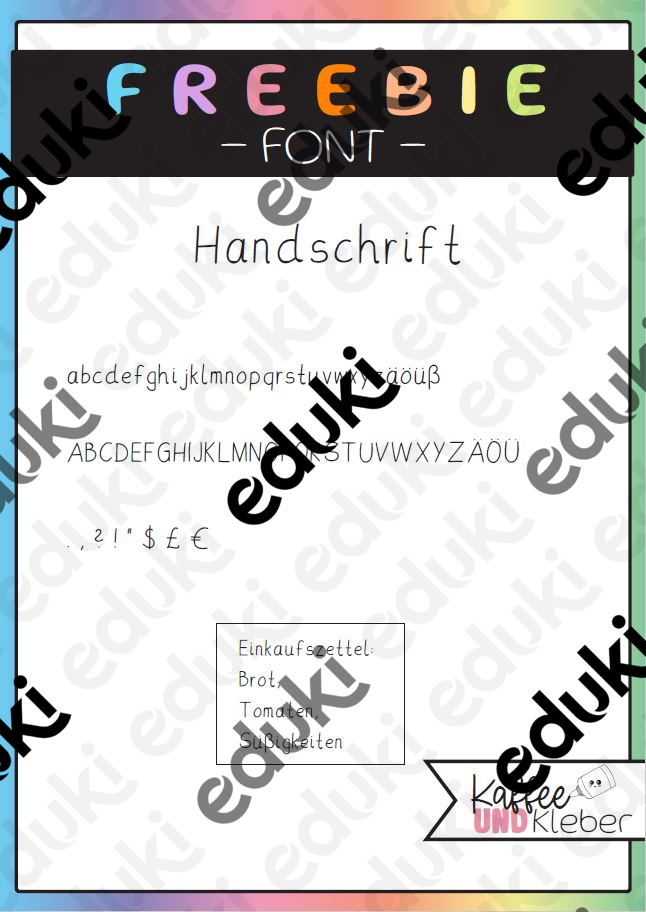
selbst erstellte Schriftarten - Font: Handschrift by Kaffee&Kleber - Deckblatt
Eine Schriftart mit Handschriftcharakter.
Sie eignet sich z.B. als handschriftliches Element auf Arbeitsblättern:
- Schatzkarten
- geheimnisvolle Briefe
- Notizzettel
- ...
Font: Handschrift by Kaffee&Kleber